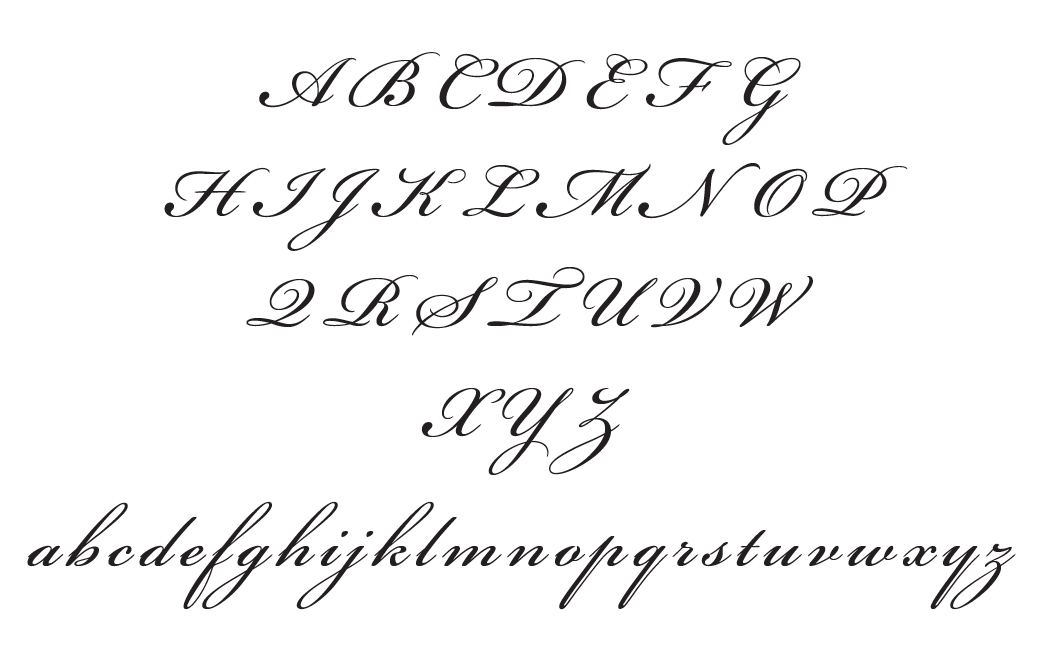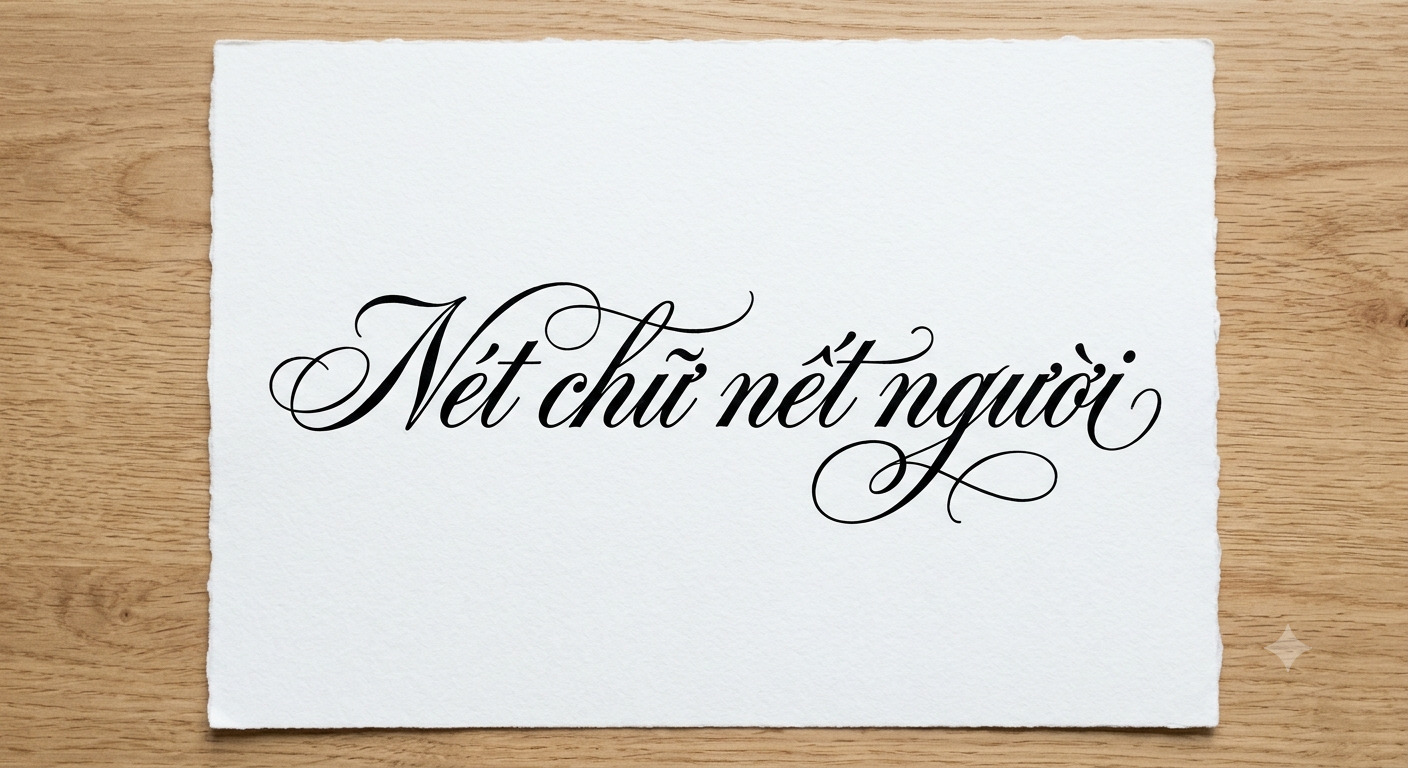
Bickham Script Pro Font là kiểu chữ Script cao cấp nổi bật với các đường nét bay bổng, mềm mại và mang đậm phong cách thư pháp châu Âu. Font chữ này thường được sử dụng trong các thiết kế yêu cầu sự sang trọng như logo thương hiệu, thiệp mời, bao bì quà tặng cao cấp và các ấn phẩm nhận diện doanh nghiệp. Tuy nhiên, nhiều phiên bản font trên Internet chưa được Việt hóa hoàn chỉnh, dễ gặp lỗi thiếu dấu, sai ký tự hoặc mất cân đối khi đưa vào thiết kế.
Font Bickham Script Pro là gì?
Bickham Script Pro là một trong những phông chữ thuộc dòng Calligraphy (thư pháp hiện đại) lộng lẫy và danh tiếng nhất thế giới, được thiết kế bởi Richard Lipton cho Adobe. Lấy cảm hứng từ những bản khắc chữ tay của các bậc thầy viết chữ thế kỷ 18, phông chữ này mang đến vẻ đẹp uyển chuyển, bay bổng và đầy chất nghệ thuật quý tộc. Đây là lựa chọn hàng đầu cho thiết kế chứng chỉ, bằng khen, thiệp cưới cao cấp, logo nhãn hàng mỹ phẩm xa xỉ và nắp hộp quà tặng yến sào.
Vẻ đẹp của Bickham Script nằm ở hệ thống các ký tự thay thế (Glyphs) và đường nối (Ligatures) vô cùng đa dạng, giúp mỗi từ viết ra như một bức tranh thư pháp thực thụ. Hiện nay, phiên bản Bickham Script Pro 3 đã cải tiến vượt bậc về số lượng họa tiết trang trí, giúp các designer thỏa sức sáng tạo. Tại thị trường Việt Nam, bản SVN Bickham Script Pro việt hóa là sự lựa chọn phổ biến nhất vì đã được xử lý hoàn hảo các dấu thanh, đảm bảo tính thẩm mỹ đồng bộ cho các ấn phẩm in ấn cao cấp tại Xưởng In Viva.
Lưu ý: Bickham Script Pro có cấu trúc nét thanh cực mảnh. Khi thiết kế in ấn trên chất liệu túi vải canvas hay túi giấy Kraft nhám, designer nên tăng nhẹ độ dày Stroke để chữ không bị mờ nhòe do độ thấm mực.
5 ứng dụng font Bickham Script Pro trong thiết kế và in ấn
Với phong cách thư pháp mềm mại, sang trọng và mang đậm dấu ấn quý tộc, Bickham Script Pro phù hợp với nhiều sản phẩm bao bì, quà tặng và ấn phẩm thương hiệu cao cấp:
- Thiết kế hộp quà tặng cao cấp: Bickham Script Pro phù hợp để thể hiện tên thương hiệu trên nắp hộp quà, đặc biệt khi kết hợp cùng kỹ thuật ép kim giúp tạo cảm giác sang trọng và tinh tế.
- Thiết kế thiệp tri ân, thư mời sự kiện: Những đường nét uốn lượn của font giúp các mẫu thiệp cảm ơn, thư mời khách hàng VIP hoặc sự kiện doanh nghiệp trở nên trang trọng hơn.
- In logo trên quà tặng gốm sứ: Font Bickham Script Pro khi in logo trên ly sứ, bộ ấm chén hoặc quà tặng đối tác giúp sản phẩm mang vẻ đẹp cổ điển, thanh lịch.
- Khắc laser quà tặng kỷ niệm: Các đường nét mềm mại của font tạo điểm nhấn khi khắc trên pha lê, gỗ hoặc kim loại, giúp sản phẩm cá nhân hóa trở nên cao cấp hơn.
- Thiết kế bao bì sản phẩm cao cấp: Bickham Script Pro giúp nhãn dán hũ yến, mật ong hoặc các dòng quà tặng sang trọng tạo cảm giác tinh tế, khác biệt.
5 lưu ý khi sử dụng font Bickham Script Pro
Để font Bickham Script Pro giữ được vẻ đẹp thư pháp khi ứng dụng vào thiết kế và in ấn thực tế, designer cần chú ý các yếu tố sau:
- Kiểm soát độ chồng lấp của nét chữ: Bickham Script Pro có nhiều đường nét uốn lượn, vì vậy cần kiểm tra các điểm giao nhau để tránh tình trạng mực bị dồn hoặc mất chi tiết khi in.
- Tối ưu đường Path khi gia công bế nổi: Chuyển đổi font sang dạng vector giúp xử lý chính xác các nét cong, đảm bảo logo hoặc tên thương hiệu giữ được độ mềm mại khi dập nổi trên hộp quà cao cấp.
- Lựa chọn kích thước chữ phù hợp: Do có nhiều nét thanh mảnh, không nên sử dụng font ở kích thước quá nhỏ vì dễ làm mất nét khi in Offset hoặc in trên chất liệu có độ hút mực cao.
- Chọn màu sắc và kỹ thuật gia công phù hợp: Bickham Script Pro phù hợp với các hiệu ứng như ép kim vàng, ép kim bạc, phủ UV để làm nổi bật đường nét thư pháp và tăng giá trị thẩm mỹ cho sản phẩm.
- Cân chỉnh bố cục khi thiết kế: Các nét kéo dài của font có thể chiếm nhiều diện tích, vì vậy cần bố trí khoảng trống hợp lý để logo, slogan hoặc thông điệp không bị rối mắt.